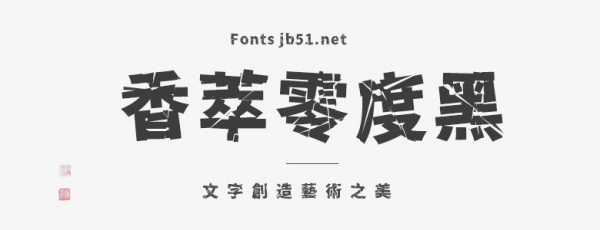
香萃零度黑是日文字體【零ゴシック】的簡(jiǎn)化字補(bǔ)齊版本。字體的沖擊性很強(qiáng),具有非常獨(dú)特的個(gè)性,切割與扭曲明顯。本字體屬于開(kāi)源項(xiàng)目,允許全社會(huì)免費(fèi)使用。
在字體的筆畫(huà)上做了扭曲、分裂的設(shè)計(jì),在切口處呈現(xiàn)遠(yuǎn)看曲線(xiàn)、近看直線(xiàn)的效果??紤]到作為裝飾性字體,(在不影響辨識(shí)的情況下)部分日本漢字字形仍然保留。根據(jù)簡(jiǎn)體中文書(shū)寫(xiě)習(xí)慣,微調(diào)了標(biāo)點(diǎn)的位置。目前有近7000簡(jiǎn)化字。
破碎的字體像冰面紋理。源字體名【零ゴシック】,ゴシック即gothic,意為黑體字,香萃零度黑由此得名。